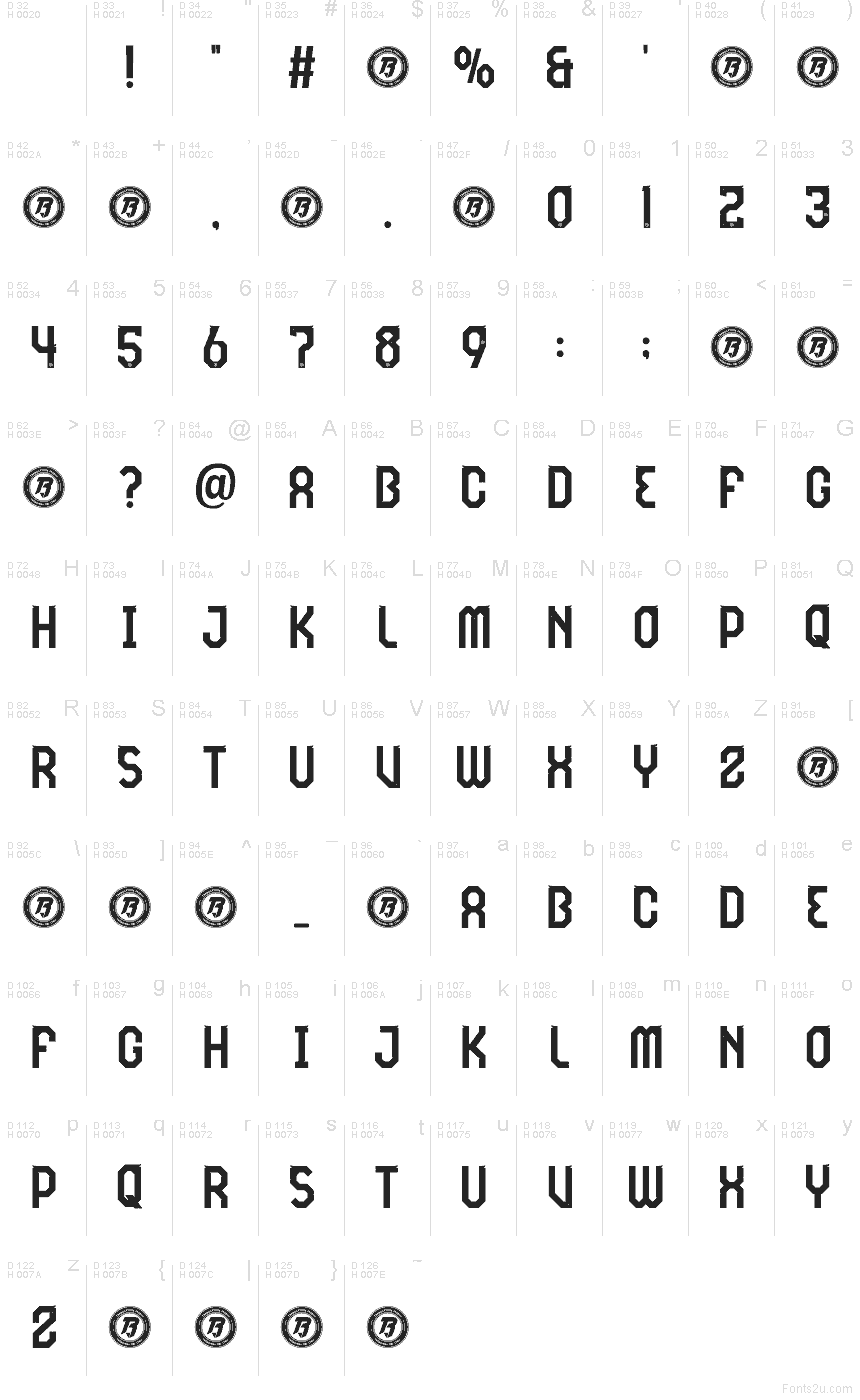
Feijenoord es una tipografía display de estilo techno, gratuita y creada por Trequartista Studio, que fusiona letras de bloque futuristas con un marcado aire blackletter. Las mayúsculas parecen cortadas de paneles rígidos, con esquinas recortadas, muescas profundas y una banda interna que se repite, otorgando a las letras un ritmo mecánico y fragmentado.
Es perfecta para titulares de pósteres, gráficos de videojuegos, branding deportivo, portadas de álbumes y títulos de eventos donde ese toque urbano y blindado ayuda a transmitir el mensaje. Como fuente gratuita, también funciona muy bien en monogramas y textos cortos, ya que los trazos superpuestos y los giros angulares dotan a las letras de una fuerte presencia gráfica.